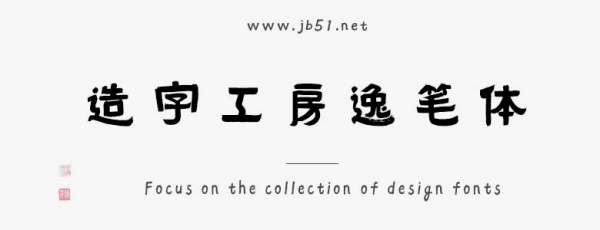
造字工房逸筆體由上首造字字庫出品的字體,兼?zhèn)涔艠闱轫嵟c現(xiàn)代風(fēng)格。字形保留了隸書方直的形態(tài)特點,筆畫飄逸。適合應(yīng)用于平面宣傳設(shè)計、網(wǎng)頁設(shè)計,書法字帖等領(lǐng)域,需要的朋友可以前來本站下載。
造字工房逸筆體,取法隸書古韻,融合現(xiàn)代漢字設(shè)計創(chuàng)作而成,兼?zhèn)涔艠闱轫嵟c現(xiàn)代風(fēng)格。字形保留了隸書方直的形態(tài)特點,筆畫飄逸,有著自然的彎曲和粗細(xì)變化,隨意卻又不失美感,恰似書法家揮毫之際的逸興遄飛。本字體為簡體字庫,采用OpenType/CID格式,Adobe-GB1-5編碼?;谥腥A人民共和國GB2312-80字符集標(biāo)準(zhǔn),另按需添加101個漢字。共收容字?jǐn)?shù)6864CJK漢字,ASCII常用字符100個。